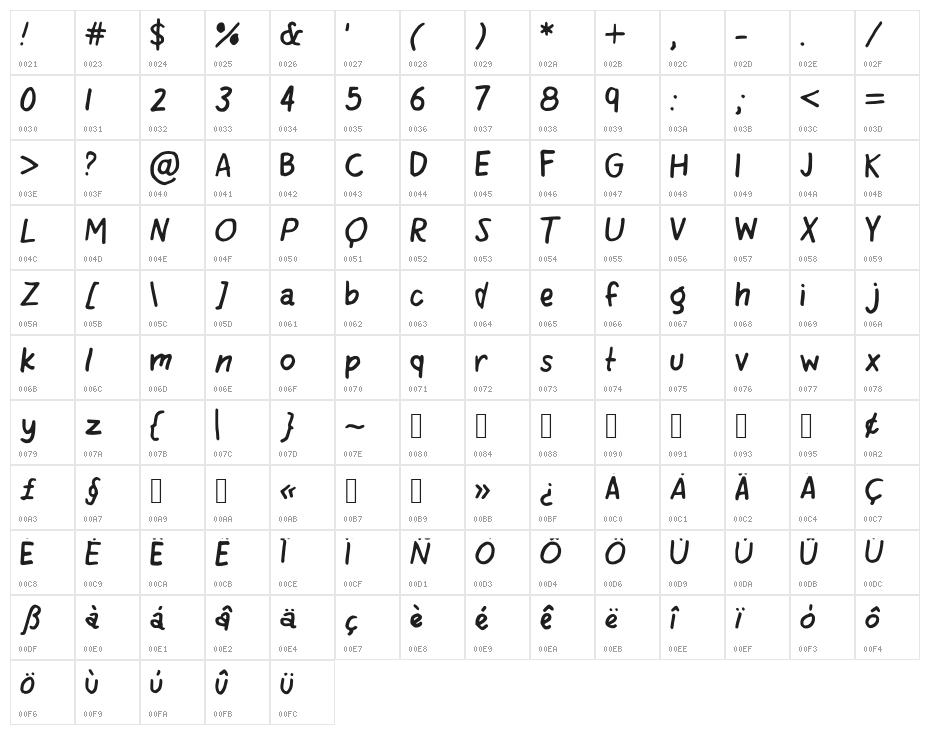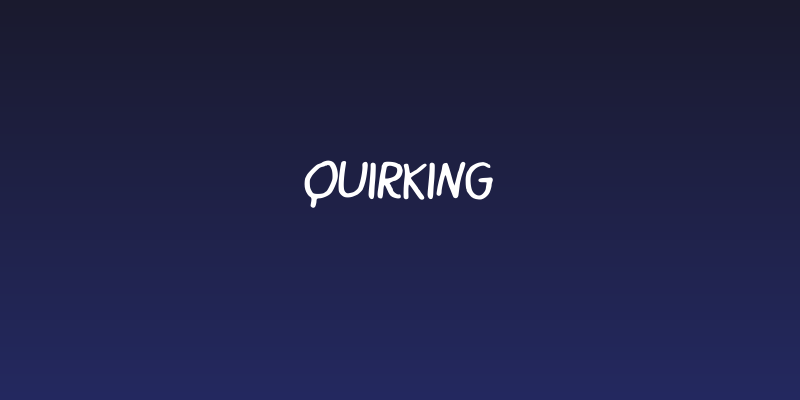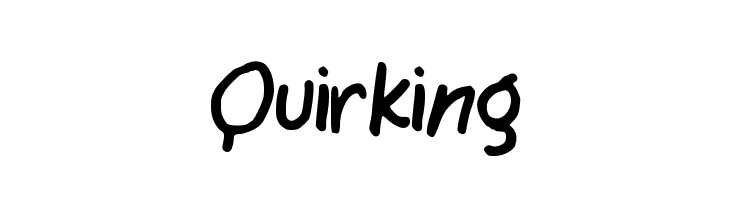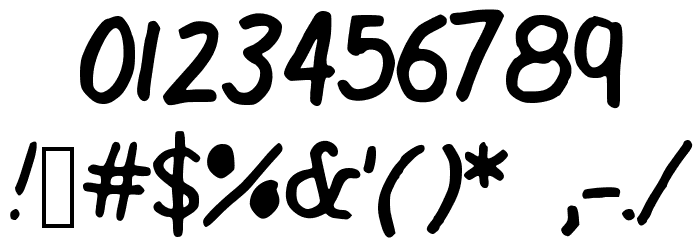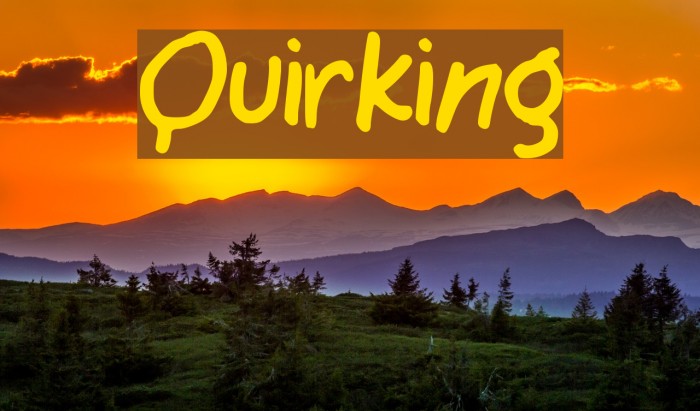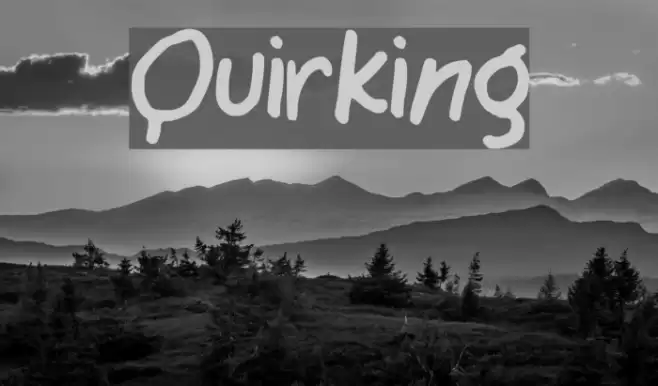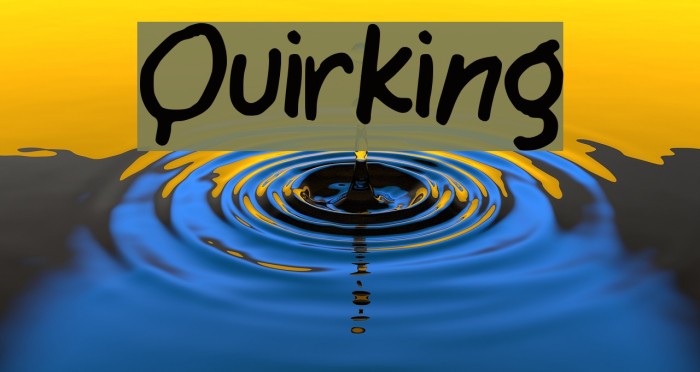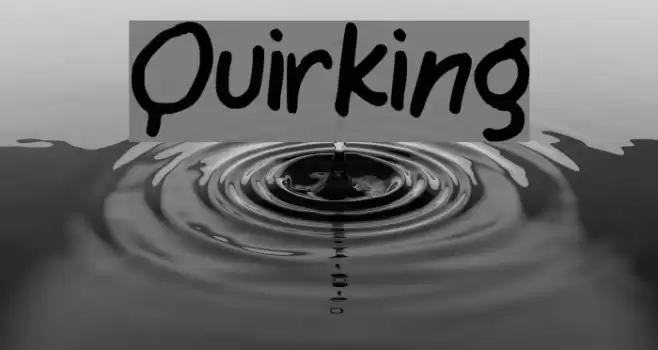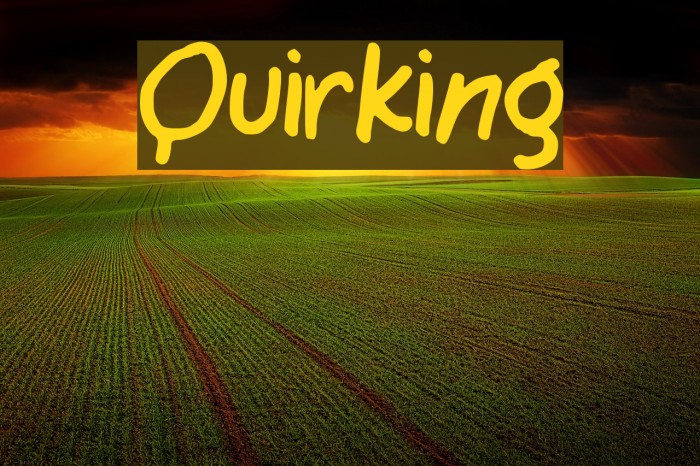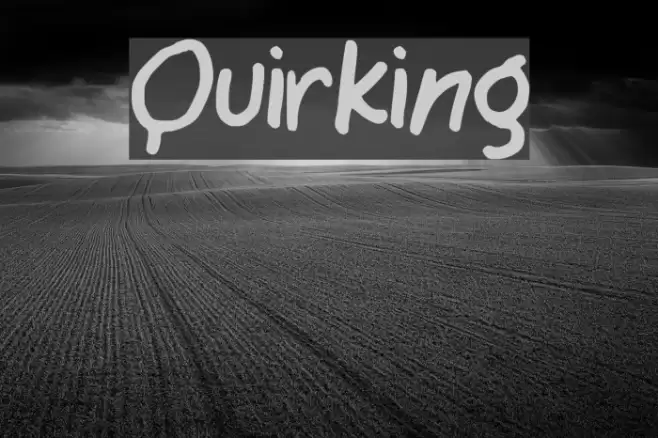
Quirking Font
| Cas d'utilisation | Headlines, Logos, Informal Text |
| Projets proposés | Ideal for greeting cards, children's books, playful branding, and social media graphics. |